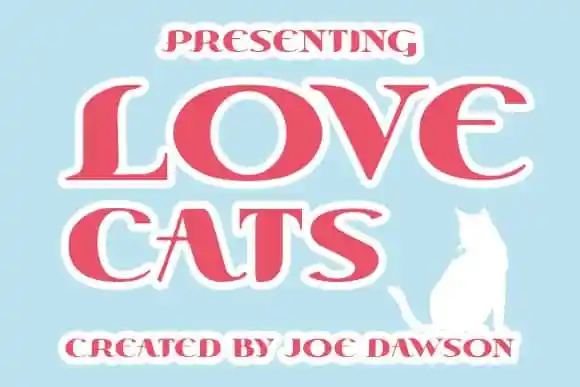
Love Cats Display Font – Fonte Grátis
Love Cats Display Font
Aproveite para dar vida aos seus projetos com a Love Cats Display Font, uma fonte display que traz um toque encantador ao seu design. Esta elegante seleção é perfeita para aqueles momentos em que você deseja criar algo mais robusto e autêntico na sua identidade visual. Com um charme suave e a personalidade desenfreada, Love Cats é o tipo certo para se juntar aos seus pensamentos criativos. Esta fonte oferece uma flexibilidade impressionante, adaptável para diversos contextos de design. O seu aspecto amigável torna esta escolha ideal para um leque vasto de ideias e projetos, desde a criação de banners até ao desenvolvimento do branding corporativo. Add a touch of love to your next graphic project and watch as Love Cats Display Font elevates them effortlessly. A Love Cats Display Font não só adicionará uma camada de personalidade aos seus projetos, mas também os deixará muito mais impressionantes e memoráveis. Que tal incorporar essa fonte para dar um novo gás a seus trabalhos gráficos?